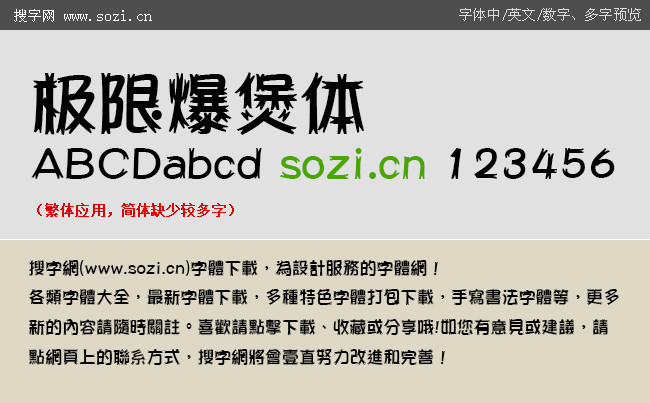
極限爆煲體
搜字網(wǎng)給大家提供一款極限爆煲體字體下載, 極限爆煲體字體是一款非常不錯的中文創(chuàng)意字體,該字體線條粗壯,簡約美觀,呈爆炸效果,字字皆生動有神,能夠適用于藝術(shù)設(shè)計、包裝印刷、平面海報設(shè)計、包裝設(shè)計等廣告應用。(本字體為個人非商用版,如需要商用請聯(lián)系作者購買版權(quán))